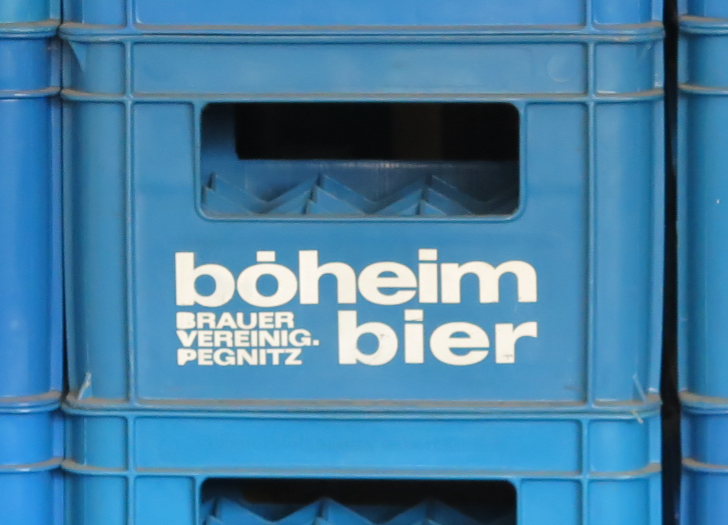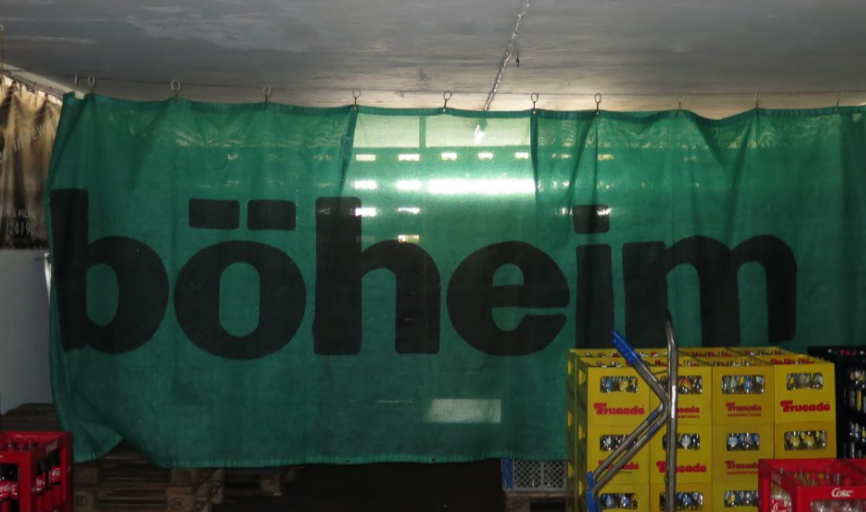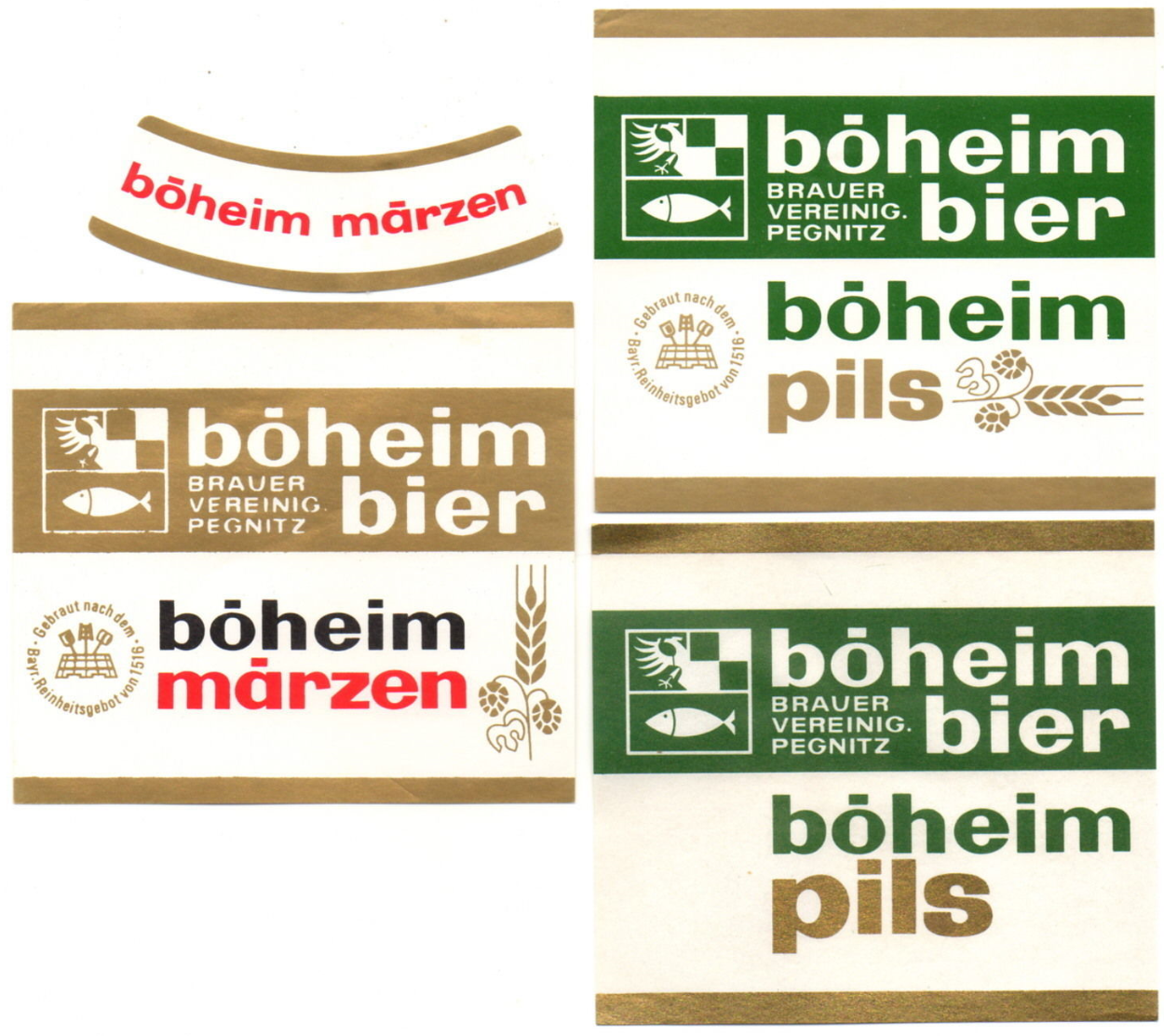
Suche Hausschrift einer oberfränkischen Brauerei von ca. 1960
vielleicht kann mir hier jemand helfen. Ich bin auf der Suche nach der Hausschrift der oberfränkischen Böheim Brauer Vereinigung aus Pegnitz. Ich befürchte das Original (Flaschenetikett) ist handgezeichnet. Eventuell hat jemand auch einen Tipp für einen ähnlichen Font, wie z.B. für den auf dem Kasten?
Der Kasten ist mit einer Helvetica Black Extended beschriftet.